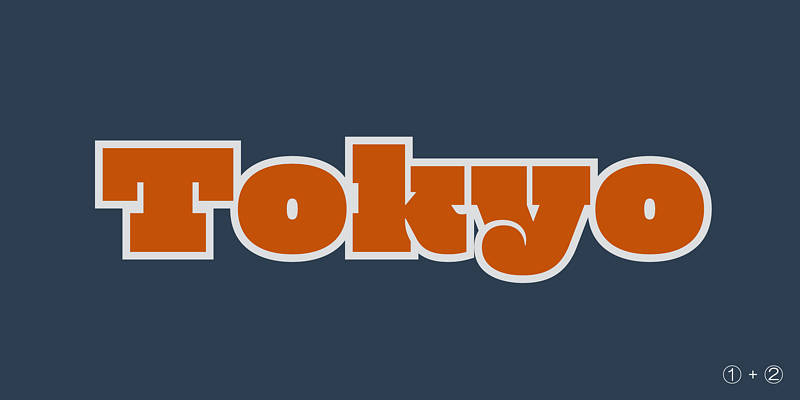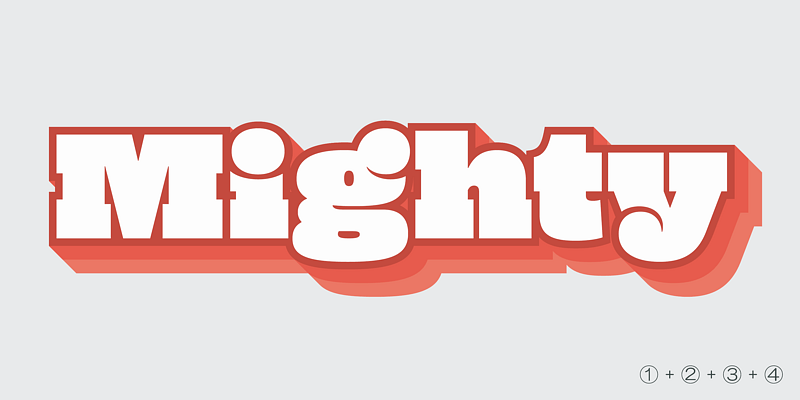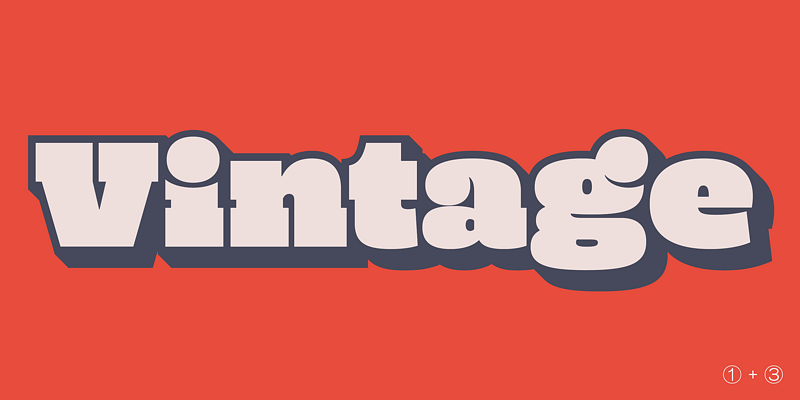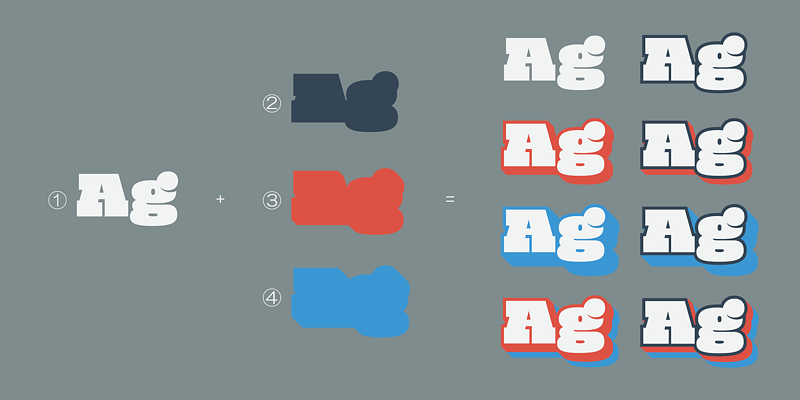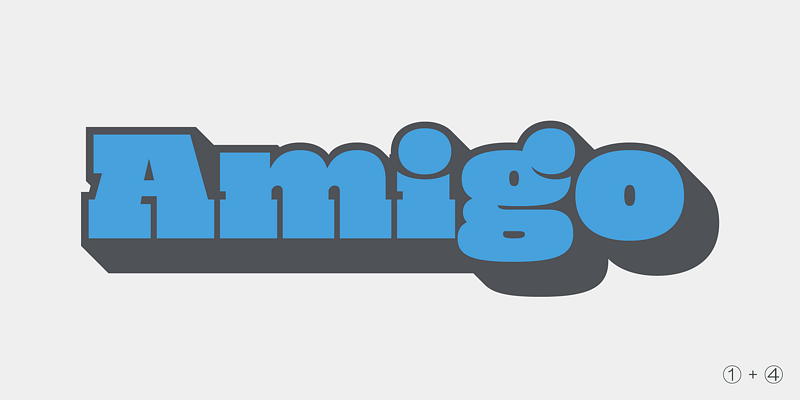
Une police colorée en 4 couches ! Empilez simplement le même texte avec chaque style dans la même position. Mighty Slab One peut également être utilisée indépendamment. Très grande hauteur d’œil pour plus de visibilité manifeste.